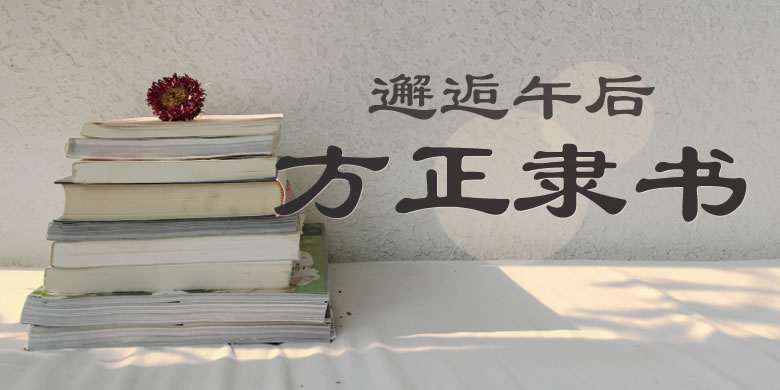
方正隶书繁体
品牌:方正字库设计师:方正字模部发行时间:1996字库编码:大陆简体(GB2312-80)、大陆繁体(GB12345-90)、简繁扩展(GBK)、港台地区(BIG-5)分类:隶书
方正隶书繁体
方正隶书来源于铅字时代的隶书,原设计是作为报刊用的标题字。这款字体笔画丰肥圆润,横笔画长、竖笔画短,字形平稳,笔画停匀。为了兼顾当代字形规范,很多结构接近楷书,与各种传统隶书书法均有较大差异,其特点更多地体现于笔画形态本身,因而属于偏现代风格的隶书字体。方正隶书已经被广泛应用于报纸标题、荧屏字幕及户外广告等。